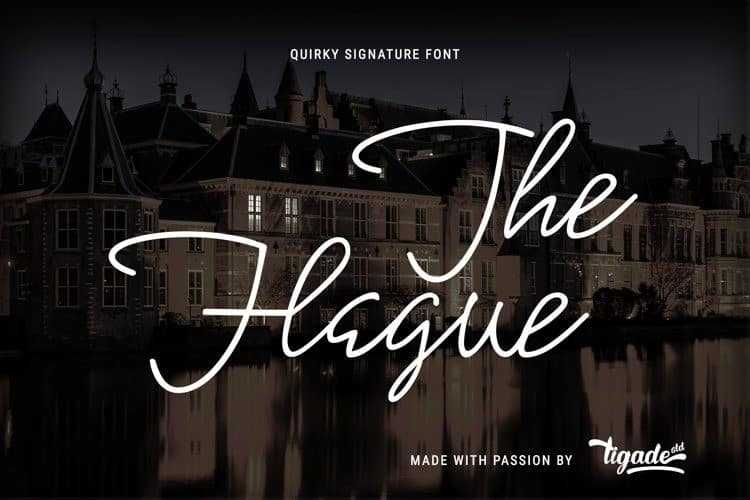
The Hague Handwritten Font – Download Grátis
A fonte “The Hague Handwritten” é uma tipografia script monoline com um estilo elegante de assinatura. Ela foi criada pelo designer Tigade Std e tem um aspecto casual mas sofisticado, tornando-a muito legível. Este não é apenas outro tipo de letra comum; é algo único e levemente original, mantendo um ar elegante e deslizante à sua forma. O ideal para uso em logomarca, identidade visual ou até mesmo cartões de visita, o “The Hague Handwritten” permite que você dê mais uma personalização única ao seu design. Perfeito para criar uma assinatura diferenciada ou qualquer tipo de elemento visual, este é um recurso perfeito para aqueles buscando algo que seja distintivo e elegante, sem perder a simplicidade e a beleza do estilo handwritten. O valor adicional deste script é sua personalidade única. Com seu traço único, ele adicionará um toque diferente ao seu design, tornando-o ainda mais original e memorável. Seja para um projeto de identidade ou criação de elementos visuais simples, a “The Hague Handwritten” é uma excelente escolha que reflete elegância e originalidade no mesmo tempo.